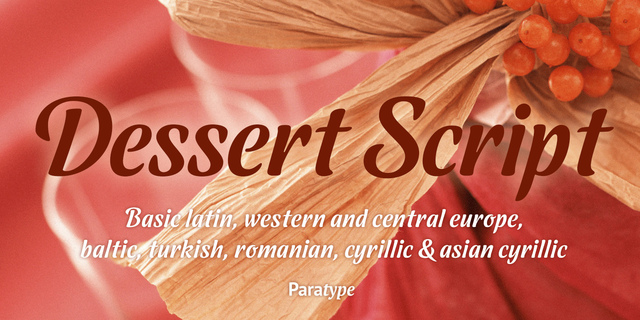
Dessert Script — псевдокаллиграфический шрифт в одном начертании, в основе которого лежит письмо плоской кистью. В шрифте удачно сочетаются мягкость контуров, общая динамика текста, дружелюбный и открытый характер. Dessert Script подходит для коротких надписей, поздравлений, кондитерских упаковок и меню. Шрифт разработан Александром Любовенко и выпущен компанией Паратайп в 2015 году.